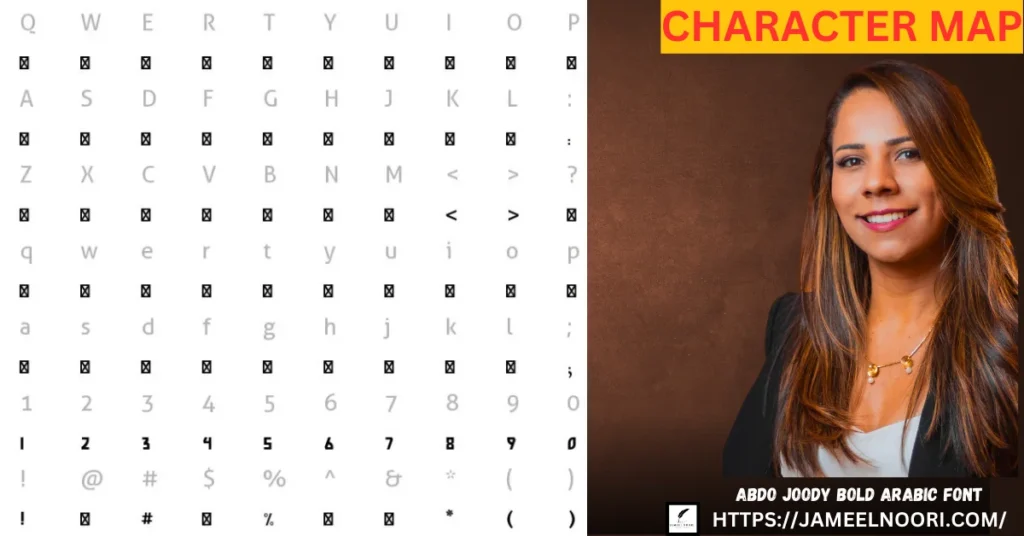
Abdo Joody Bold Arabic Font – Powerful & Visually Strong Arabic Typeface
Abdo Joody Bold Arabic Font ek powerful aur visually strong Arabic typeface hai jo modern aur traditional dono designs ke liye behtareen choice mani jati hai. Yeh font khas tor par un users ke liye design kiya gaya hai jo Arabic fonts ko professional level par use karna chahte hain, chahe woh web designers hon, graphic artists hon ya publishers. Is font ka bold style text ko zyada readable aur impactful banata hai, khas tor par headings aur titles ke liye.
What Makes Abdo Joody Bold Arabic Font a Powerful Choice
Abdo Joody Bold Arabic Font ek Bold TrueType Font hai jo apni strong strokes aur balanced letterforms ki wajah se kaafi popular ho chuka hai. Is font ko ab tak 10,171 se zyada dafa download kiya ja chuka hai aur 137 users ne isay 4.53 out of 5 rating di hai, jo iski quality aur usability ko clearly show karta hai.
Yeh font Arabic calligraphy ke rules ko follow karta hai lekin modern touch ke sath, jo isay worldwide audience ke liye suitable banata hai.
Key Features of Abdo Joody Bold Arabic Font
Abdo Joody Bold Arabic Font ki kuch standout features neeche bullet points me diye gaye hain jo featured snippet ke liye bhi optimized hain:
• Bold aur clear Arabic letter structure
• High readability for digital aur print use
• Professional calligraphy style
Yeh features isay best Arabic font category me la kar khara kar dete hain, khas tor par jab baat ho Urdu fonts aur Arabic fonts ki.
Best Uses of Abdo Joody Bold Arabic Font in Design
Abdo Joody Bold Arabic Font multiple design purposes ke liye use kiya ja sakta hai. Yeh font especially headings aur branding ke liye expert choice mana jata hai.
Common Use Cases:
• Website headings aur banners
• Islamic posters aur flyers
• Book covers aur magazine titles
• Social media graphics
• Logo design aur branding projects
Abdo Joody Bold Arabic Font character map and calligraphy style
Abdo Joody Bold Arabic Font ka character map jo Arabic letters ki clear aur balanced calligraphy show karta hai.
Character Map and Calligraphy Style of Abdo Joody Bold TTF Arabic Font
Abdo Joody Bold Arabic Font ka Character Map section bohat madadgar hai jahan se aap har letter ki calligraphy detail me samajh sakte hain. Is font ke curves aur joins Arabic script ke asli rules ke mutabiq design kiye gaye hain.
Yeh cheez isay Islamic aur educational content ke liye bhi perfect banati hai, jahan clarity aur authenticity bohat zaroori hoti hai.
Why Abdo Joody Bold Arabic Font is an Expert Choice Worldwide
Abdo Joody Bold Arabic Font sirf Pakistan hi nahi balkay worldwide designers ke darmiyan popular hai. Iski bold appearance content ko zyada attention-grabbing banati hai aur readability compromise nahi hoti.
Jo users best Arabic font ki talash me hote hain, un ke liye yeh ek complete guide solution hai jo quality aur performance dono deliver karta hai.
Agar aap ek aisa Arabic font chahte hain jo professional, bold aur visually appealing ho, to Abdo Joody Bold Arabic Font bilkul worth it hai. Iski high rating, zyada downloads aur strong calligraphy style isay market ka trusted option banati hai.
Is Abdo Joody Bold TTF Arabic Font good for Islamic content?
Yes, its calligraphy style makes it suitable for Islamic designs.
Why is this font popular among designers?
Because of its bold look, readability, and professional design.
Is it considered one of the best Arabic fonts?
Yes, many designers consider it among the best Arabic fonts available.